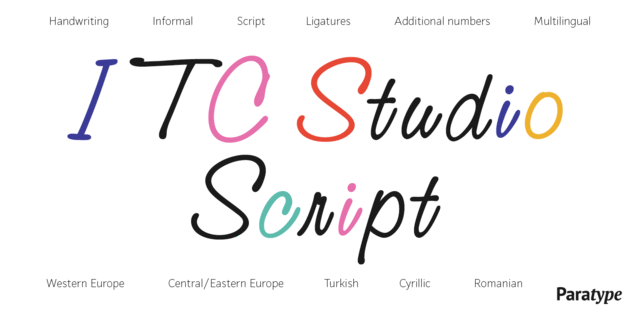
Шрифт разработан в фирме International Typeface Corporation в 1990 (дизайнер Пат Хиксон) для применения в рекламе и акциденции. В его основе лежит неформальный рукописный почерк. Кириллическая версия разработана в фирме ПараТайп (ПараГраф) в 1993 (дизайнер Эльвира Слыш).
лихой, праздничный, вежливый, красивый, тонкий, манерный, нарядный, радостный, счастливый, творческий, прелестный, симпатичный, поэтичный, артистичный, милый, дружелюбный, крафтовый, артизанальный, вкусный, добрый, мягкий, рукотворный, ручной, домашний, уютный, доверительный, зеленый, натуральный, природный, теплый, динамичный, подвижный, ламповый, аппетитный, гибкий, живой, оригинальный, приветливый, свежий, характерный, круглый, бодрый, сочный, спелый, озорной, цветочный, выразительный, приятный, летний, неформальный, эмоциональный, чувственный, вдохновенный, поэтический, лирический, колоритный, пластичный, воздушный, лиричный, ритмичный, округлый, качественный, сентиментальный, честный, здоровый, игривый, забавный, гладкий, эффектный, кучерявый, культурный, мастерский, эстетичный, кудрявый, весенний